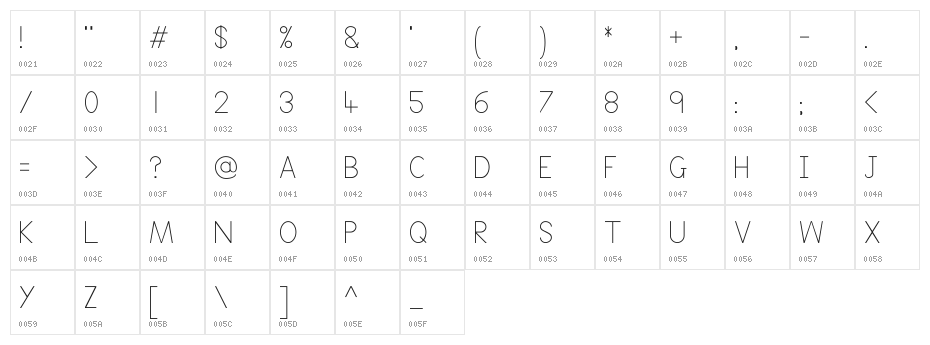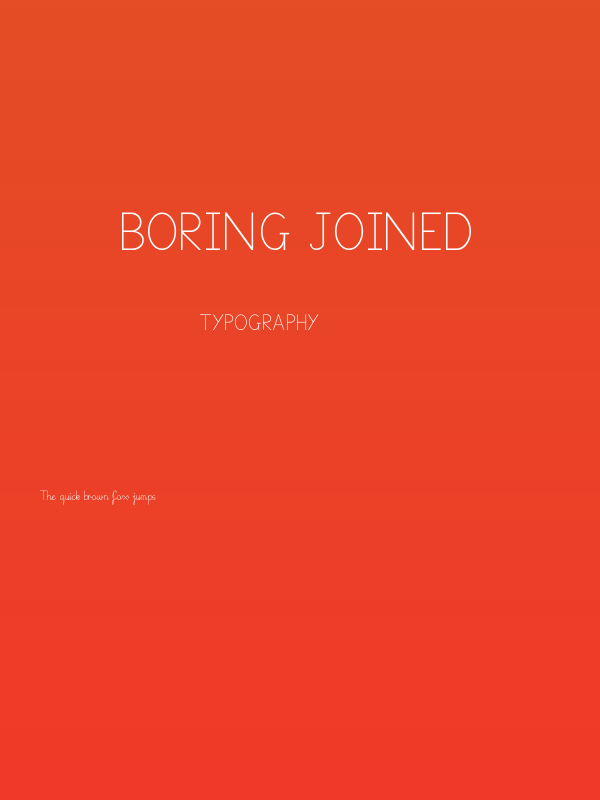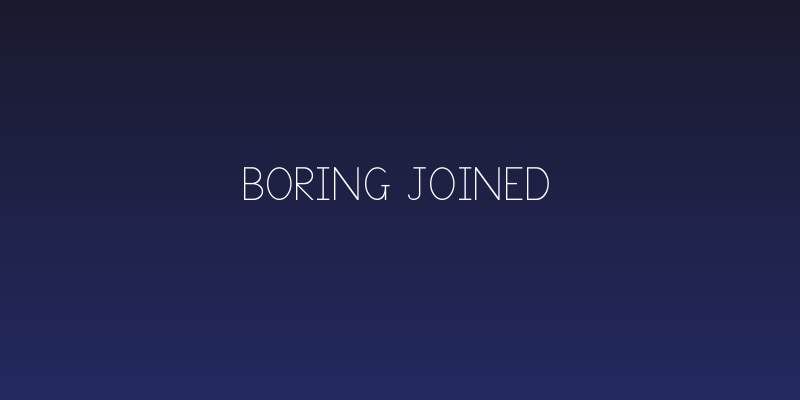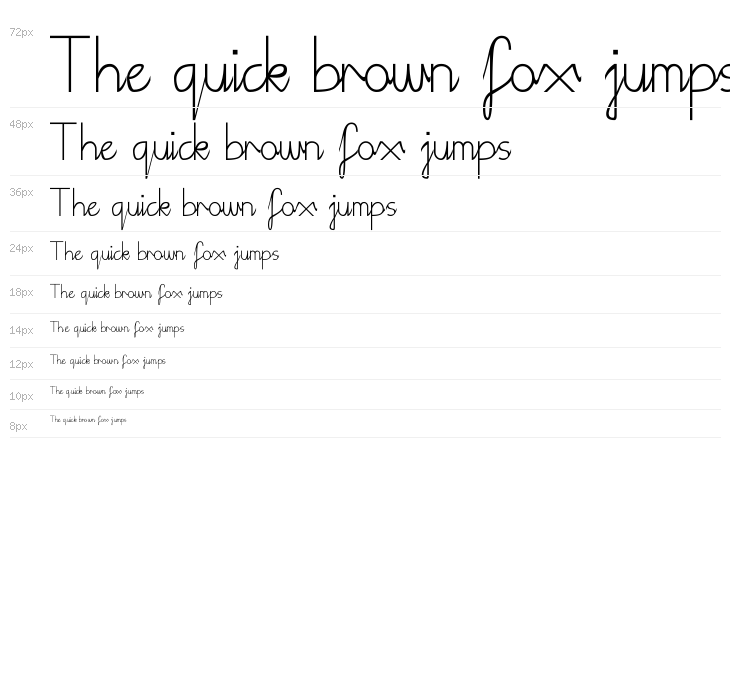
Boring Joined Font
| Anwendungsfall | Headlines, Logos, Invitations |
| Vorgeschlagene Projekte | Ideal for branding, invitations, and editorial design where a mix of modern and personal touch is desired. |